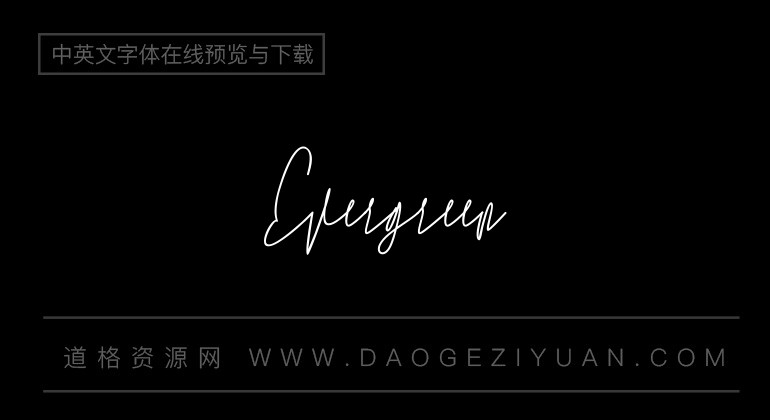
Evergreen 是一款由英国设计师 Dan Rhatigan 创作的字体,它具有简洁、稳重、优雅的特点。Evergreen 字体有着清晰的结构,细节处理精细,能够轻松表达出深情、宁静、温柔的气质。它的字体结构较为简洁,适合用于报纸、杂志、书籍、广告等等,也可以用于网页设计,能够给人以清新的感觉。内容介绍
Evergreen是一款非常不错的手写艺术字体,具有很好的视觉感,适合于文化类的宣传设计、商业类品牌的广告和产品包装设计以及个性化文字排版等较多场景。